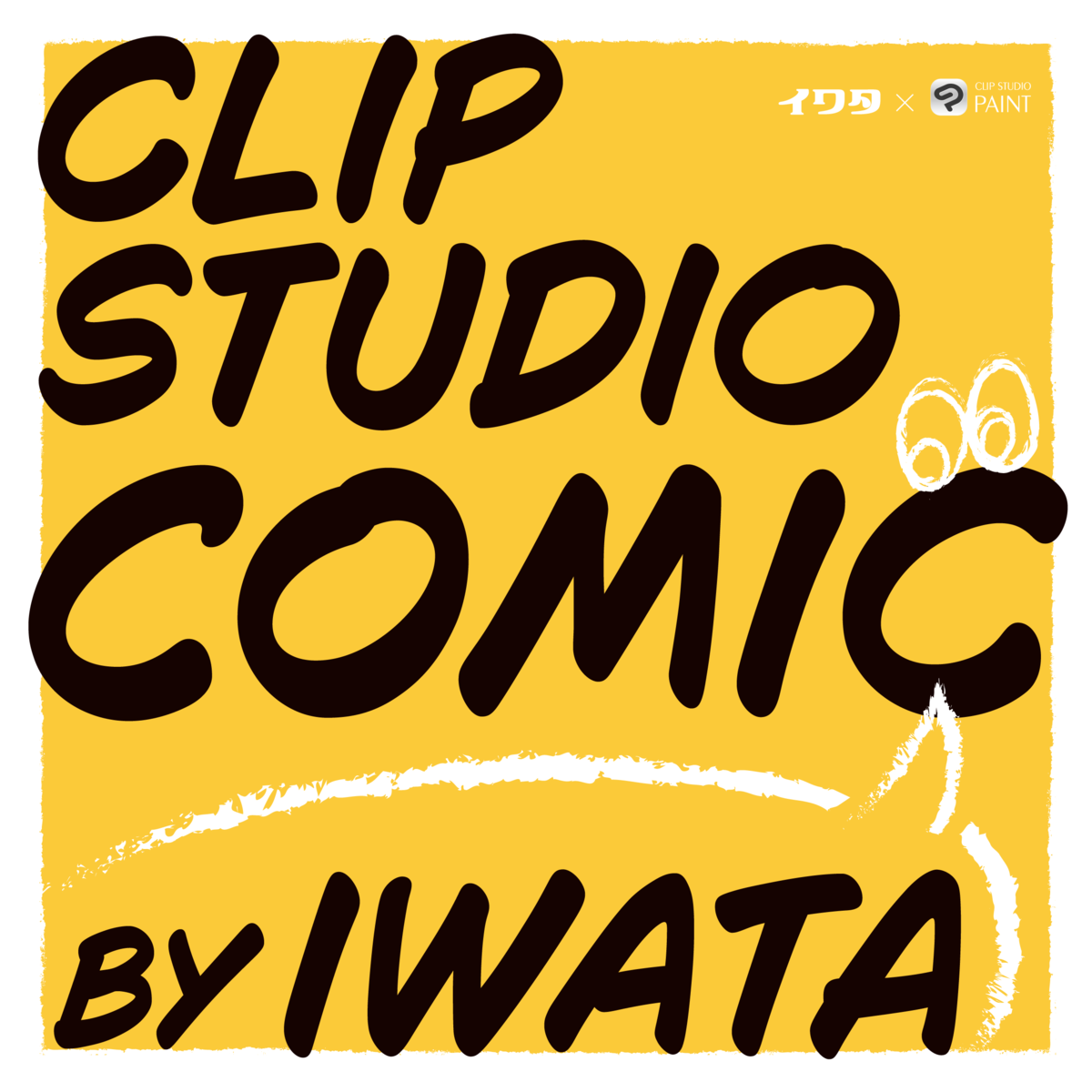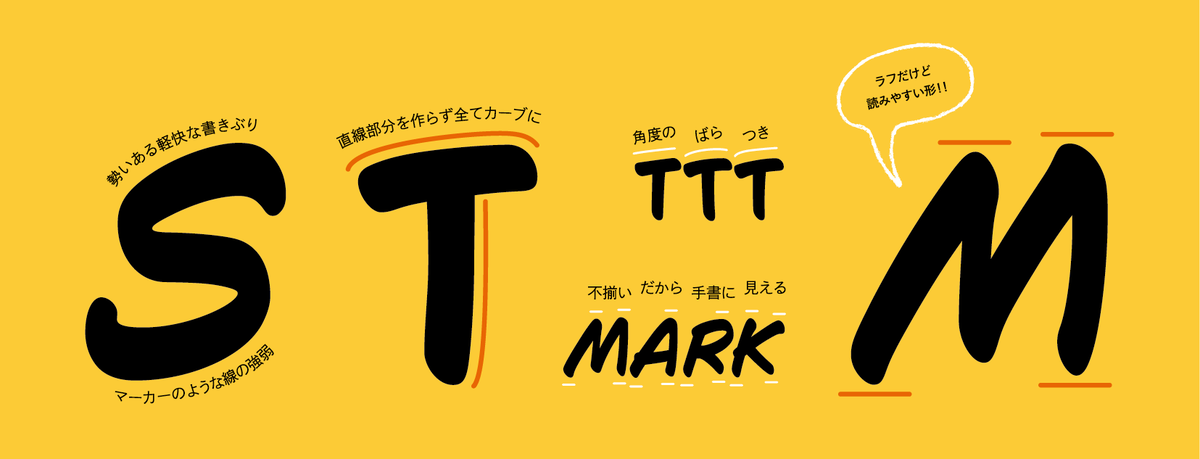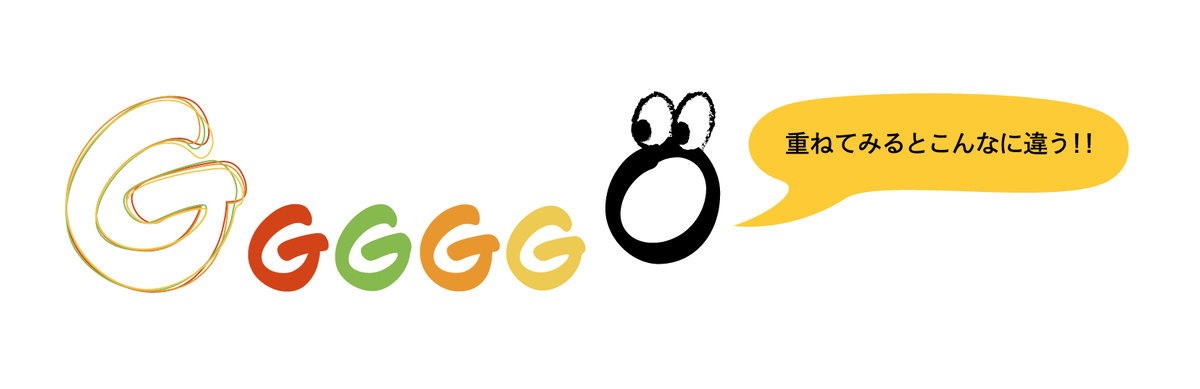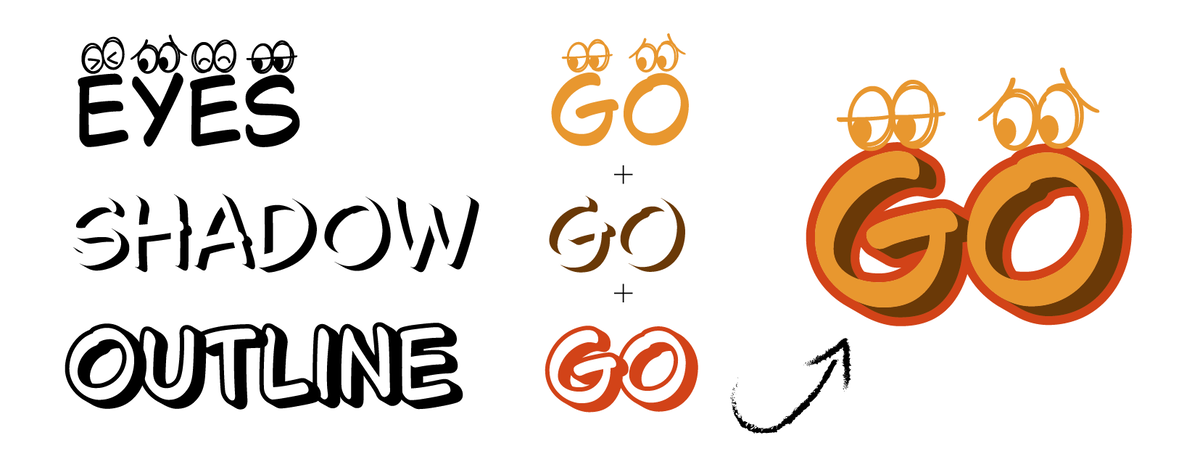
CLIP STUDIO PAINT搭載フォント「Clip Studio Comic」、一般販売を開始。手書きの揺らぎと遊び心をそのままに、20スタイルを展開。「Clip Studio Comic」に加え、Outline/Shadow/Eyesなどの表情豊かな「Iwata Clip Studio Comic」ファミリーを同時発売
イワタは、セルシスが提供するイラスト・マンガ・Webtoon・アニメーション制作アプリ「CLIP STUDIO PAINT」に搭載されている欧文フォント「Clip Studio Comic」の一般販売を開始したことを2025年6月5日に発表した。
「Clip Studio Comic」は、CLIP STUDIO PAINTのブラシツールを使って書かれたラフスケッチを元に開発された、手書き風の欧文書体。
文字ごとに線の強弱や高さの揺らぎを取り入れ、手書き特有の自然さや親しみやすさを表現。
1文字に4つの字形を持たせてランダムに切り替える仕様や、欧米ユーザーの声を反映した、文脈に応じて大文字「I」をCrossbar I(上下に横線付き)へ自動変換する機能など、リアルな表現を追求している。
また、今回の一般販売では、CLIP STUDIO PAINT Ver.3.0以降に搭載されている「Clip Studio Comic」に加え、縁取りの「Outline」、影のみの「Shadow」、目を加えたユニークな「Eyes」など、多彩なスタイルを収録した「Iwata Clip Studio Comic」ファミリーを展開。
計20フォントで、POPで遊び心あるデザインを幅広くサポートする。
手書き特有のラフさをリアルに再現
マーカーで描いたような線の強弱や、文字ごとに角度や高さにわずかな違いを持たせる処理、さらに直線を使わず緩やかなカーブで構成された字形によって、やわらかさと親しみやすさを演出している。これに加えて、ひとつの文字に複数のバリエーションを用意し、文字を入力するたびに自動でランダムに切り替わる仕組みを導入。文章全体に自然な“揺らぎ”が生まれ、本当に手で書かれたようなラフで表情豊かなテキストが実現。
▼CLIP STUDIO PAINTのブラシツールを使用したスケッチ
▼文字ごとに揺らぎを加え、手書きらしい自然な表情を再現
ランダム表示
ひとつの文字に対して4つの異なるバリエーションを用意し、入力のたびに見た目がランダムに切り替わる仕組みを採用している。同じ文字でも毎回違う形で表示されることで、まるで手書きで書かれたような自然な“揺らぎ”が生まれる。
▼同じ文字“G”を並べた例と、重ねたときの差
この機能はOpenType機能に対応したアプリケーションであれば、特別な設定や操作をすることなく自動で有効になる。
文脈に応じて「I」の形が自動変換
英語では、人称代名詞「I」の視認性を高めるために、上下に横線(クロスバー)のついた「Crossbar I」が使われることがある。
「Clip Studio Comic」では、入力された文章の文脈を自動的に判断し、「I」が一人称代名詞である場合に、Crossbar Iに変換される。
通常の「I」(縦棒)と使い分けることで、読みやすさが向上し、欧米コミックらしい自然な表現に。開発時に行ったネイティブユーザーへのアンケートでも、要望の多かった機能。
▼文中の「I」が文脈に応じて異なる形で表示されている様子
遊び心満点!Outline・Shadow・Eyesなど多彩なスタイルを新たに追加
イワタDX版では、定番の「Regular」「Italic」「Bold」「Bold Italic」に加えて、目を引く「Outline」、立体感を演出する「Shadow」、ユーモラスな目のついた「Eyes」を収録し、遊び心と表現力を兼ね備えた多彩なスタイルを追加。
雑誌の見出し、パッケージデザイン、Web・動画制作など、幅広いシーンでの活躍が期待できる。
▼「Outline」「Shadow」「Eyes」などを自由に組み合わせてオリジナルの表現を
30近い言語に対応
英語、フランス語、スペイン語、ドイツ語、イタリア語などラテンアルファベット圏の多くの言語表記をカバーしている。
▼Clip Studio Comicの対応言語